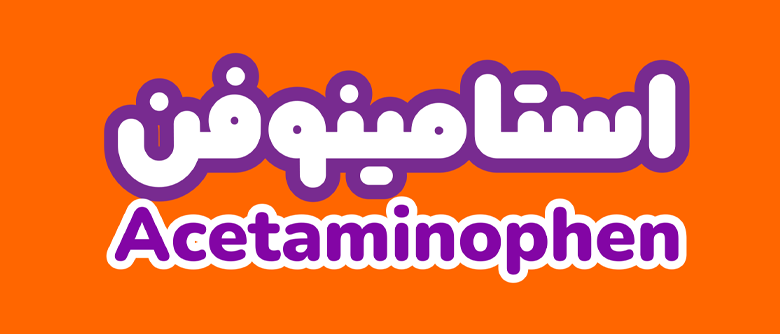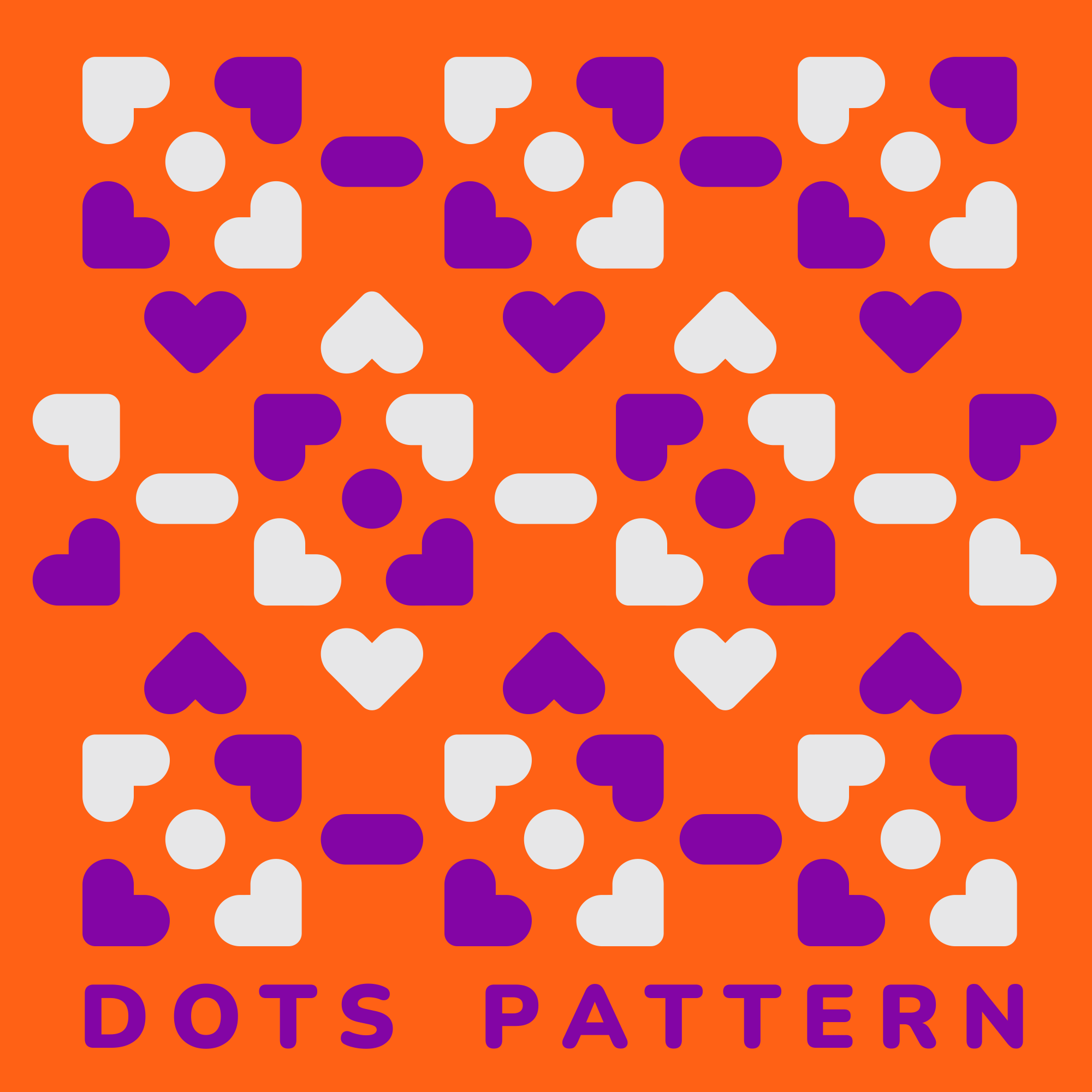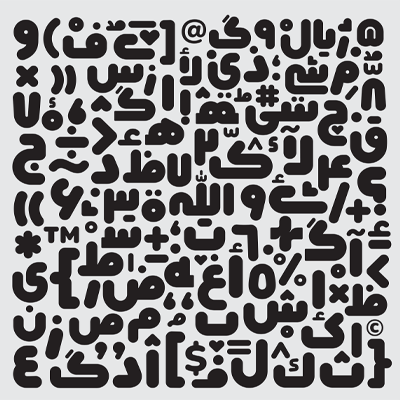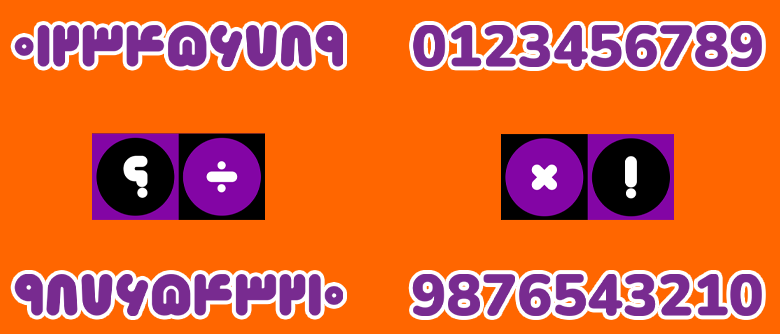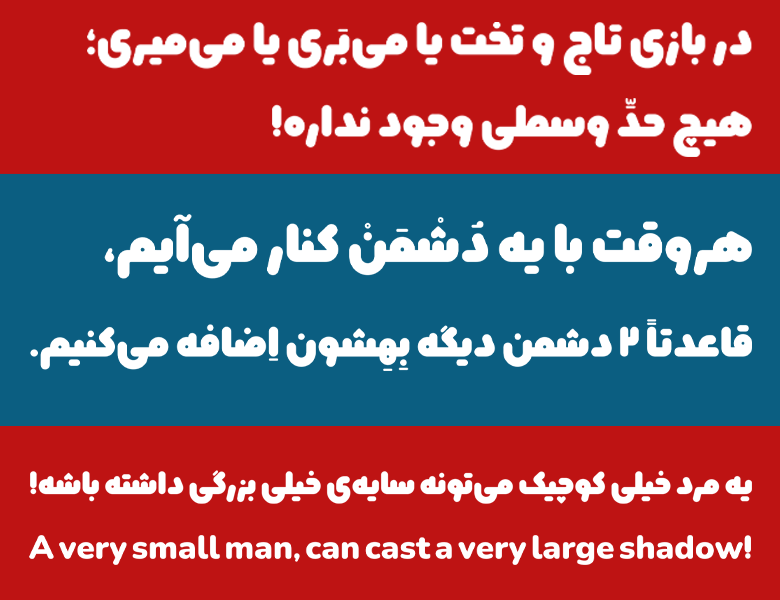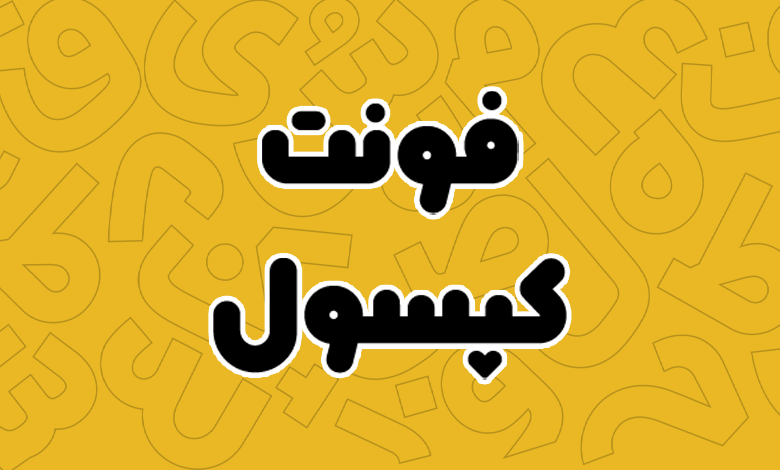
فونت کپسول (Capsule)
فونت کپسول (Capsule) را میتوان در دسته فونتهای هندسی و فانتزی قرار داد که مناسب برای تبلیغات و بستهبندی محصولات است. این فونت توسط فرهود مقدم با ساختاری هندسی و نمایشی که دارای طراحی گرد، ضخامت یکسان و سرشار از انواع منحنی در گوشههای حروف است طراحی شده و توسعه آن نیز توسط شهرزاد اکبری صورت گرفته است.
اینکه طراح برای ساخت این فونت از چه چیزی الهام گرفته ذکر نشده است؛ اما شاید عنوان آن که گویای مسئله است بیارتباط با دلیل طراحی این فونت نباشد. این فونت فانتزی دارای ظاهری کاملا مینیمال، نرم و در عین حال سنگین و تپل، مهربان و بامزه است که از آن میتوان در صنایع مختلف چاپ تا طراحی بنرها و ساخت محتواهای بصری استفاده کرد.
در ادامه این نوشته از وبسایت فونتچی به بررسی کامل فونت کپسول خواهیم پرداخت؛ فونتی با کنتراست و پهنای بسیار بالا که تنها در یک وزن طراحی شده تا نیاز بازار در صنایع مختلف را خصوصا در زمینه محصولات غذایی تامین نماید.
معرفی و بررسی فونت کپسول (capsule)
ساختار بامزهای که فونت کپسول دارد آن را به انتخابی عالی برای تایپ انواع متون بر روی بستهبندی محصولات، خصوصا محصولاتی در صنایع غذایی تبدیل کرده است. جدای از این، میتوان این فونت فانتزی را در فروشگاهها، کتابهای کودک، برندهای تجاری و تصویر سازی با اهداف مختلف مورد استفاده قرار داد.
وزن و استایل فونت کپسول
فونت کپسول فقط در یک وزن سیاه که ساختاری کاملا ضخیم دارد طراحی شده است و در فرمت TTF قابل استفاده است. این فونت فرمتهای دیگری را پشتیبانی نمیکند و همین فرمت برای استفاده در انواع سیستم عامل و نرمافزارهای گرافیکی قابل استفاده است.
منحنیهایی با درجه چرخش بالا، ساختاری کاملا یکپارچه در طراحی ضخامت حروف و امکان استفاده از انواع نقطهگذاری که به صورت گرد، جدا از هم و ساختار قلبی هستند.
مزایا و ویژگی فونت capsule
پشتیبانی از زبان عربی و انگلیسی
فونت کپسول فارسی دارای طراحی کاملا اختصاصی حروف است که همین سبک طراحی در زبان عربی و انگلیسی نیز پیاده سازی شده است.
برای زبان عربی امکان استفاده از اعراب و برخی کاراکترهای خاص که جزو زبان فارسی نیستند به صورت ترکیبی در کنار فونت فارسی قرار داده شده است. یعنی فونت کپسول عربی و فارسی ساختاری یکپارچه دارند که عربی کاملکننده نسخه فارسی است تا امکان استفاده از اعداد «۴، ۵ و ۶» و برخی اعراب که در زبان فارسی وجود ندارد قابل استفاده باشد.
برای زبان انگلیسی نیز همین سبک طراحی درنظر گرفته شده است. اما میتوان گفت که از برخی فونتهای انگلیسی برای طراحی آن الهام گرفته شده است تا ساختاری نزدیک و یکپارچه به نسخه فارسی فونت کپسول داشته باشد.
دارای سبک خاص در نقطه گذاری
نقطه گذاری در فونت Capsule به صورت تمام گرد است و خبری از گوشههای تیز در نقاط وجود ندارد. اما طراح برای اینکه خلاقیتی هم در این فونت پیادهسازی شده باشد، این امکان را فراهم کرده تا از چند سبک نقطهگذاری در این فونت بتوانید استفاده کنید که در تصویر Gif آن را میبینید.
نقطهگذاری در فونت کپسول علاوه بر نقاط معمولی گرد، دارای نقاط گرد به سبک پترن بههم چسبیده (برای نقاط دوتایی در حروفی مثل «ت») و نقاطی به شکل قلب برای حروف سهنقطه مانند «چ، پ، ث، ژ» است. این نقاط هم برای زبان فارسی و هم عربی قابل استفاده هستند.
حروف جایگزین و کاراکترها در فونت کپسول
فونت کپسول از حروف جایگزین نیز پشتیبانی میکند. این سبک از تایپوگرافی به شما این امکان را خواهد داد که حروفی همچون «ک، گ، ی، ه» و چند حروف دیگر را به سبکهای متفاوتی تایپ کنید.
علاوهبر این به صورت پیشفرض برخی ترکیبات حروف نظیر «سی، شی، صی، ضی، ـر، ـز، ـژ و…» نیز از این ترکیبات پشتیبانی میکنند تا ساختاری متفاوت را از نظر تایپ برای کلمات به شکل خاص برایتان فراهم آورند.
کاراکترهای خاص و نمادها در این فونت نیز جای گرفته است. کاراکترهایی نظیر «!، ریال، ×، *، ^ و…» که در تصویر نیز شمخص شده، با پیروی از ظاهر پهن و گرد این فونت طراحی گردیده که میتوانید از آنها چه برای زیبا سازی چه تایپ کاراکترهای خاص استفاده کنید.
تایپ اعداد فارسی و لاتین متناسب با زبان
بسته به اینکه از زبان انگلیسی یا فارسی استفاده کنید، این فونت امکان تایپ اعداد را برای هر زبان نیز فراهم کرده است. فاصله گذاری اعداد به شکل استاندارد تعیین شده است که میتوانید چه در حروف فارسیو چه انگلیسی آنها را با استفاده از صفحه کلید مختص همان زبان تایپ کنید.
عملگرهای ریاضی همچون جمع، منها، ضرب، تقسیم و سایر کاراکترهای خاص نیز به منظور هماهنگی با فونت فارسی کپسول همان طراحی با نقاط گرد و ضخامت یکسان در سرتاسر بخشها را دارند.
فونت کپسول همانطور که ذکر شد مناسب تبلیغات و متنهای کوتاه است و استفاده از آن برای متنهای بلند توصیه نمیشود.